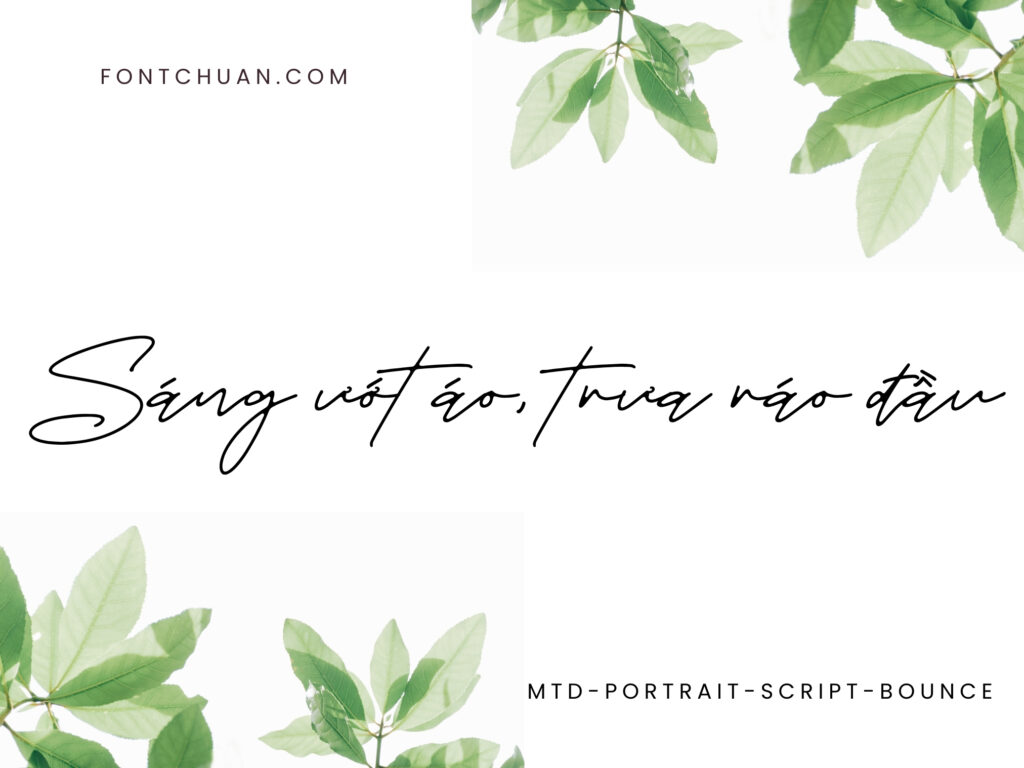
Font MTD Portrait Script Bounce Việt Hóa
Tác giả Font: Hustle Supply Co
Font MTD Portrait Script Bounce là một phông chữ script với phong cách viết tay tự nhiên và uyển chuyển. Font đã được Việt hóa bởi Mộc Hạ, hỗ trợ tiếng Việt và hơn 90 ngôn ngữ khác, giúp mở rộng khả năng ứng dụng trong các thiết kế đa ngôn ngữ. Đây là một trong những phông chữ được cộng đồng thiết kế đánh giá cao và ứng dụng trong nhiều dự án sáng tạo, đáp ứng nhu cầu đa dạng của người dùng.
MTD Portrait Script Bounce nổi bật với các đường nét mềm mại và tự nhiên, mang đến cảm giác thân thiện và gần gũi. Font rất phù hợp cho các thiết kế logo, thương hiệu cá nhân, thiệp mời, tiêu đề, bao bì sản phẩm và các ấn phẩm đòi hỏi sự tinh tế và cá nhân hóa. Các ngành nghề phù hợp bao gồm quảng cáo, giáo dục, công nghệ, thiệp cưới và ảnh cưới. Font này cũng lý tưởng cho các sự kiện như Tết, Giáng sinh, Valentine và các lễ hội khác.